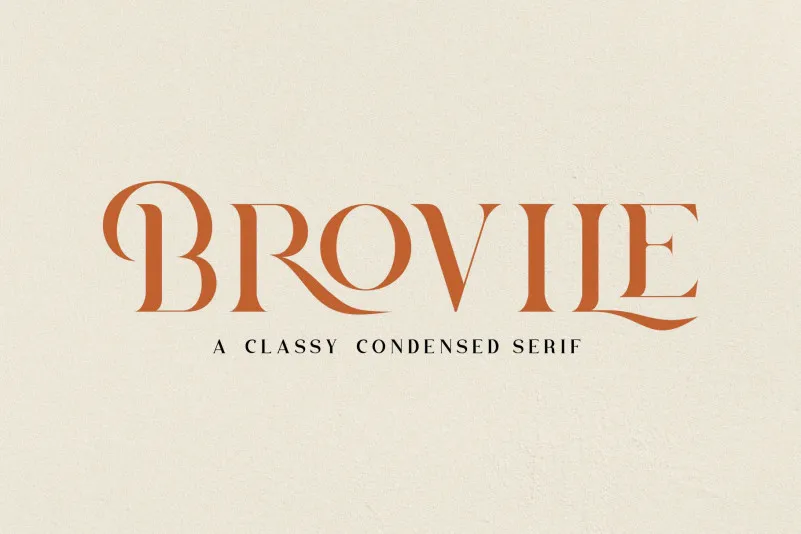
A Brovile Font é uma tipografia serifada inspirada nas estilos retro dos anos 80 combinados com toques experimentais e inovadores. Esta elegante fonte possui pequenos detalhes modernos que a tornam ideal tanto para logotipos quanto para design editorial ou web. Seu diferencial reside na interação entre as serifs afiadas e os traços finos, criando um estilo de arquitetura mid-century marcante. Com uma mistura de nostalgia e contemporaneidade, Brovile oferece um toque único que pode atrair designers profissionais, especialmente aqueles buscando algo mais inovador para seus projetos. Seja para estilizar seu website ou criar um design editorial atraente, Brovile é uma fonte poderosa e única no mercado de tipografias serifadas.